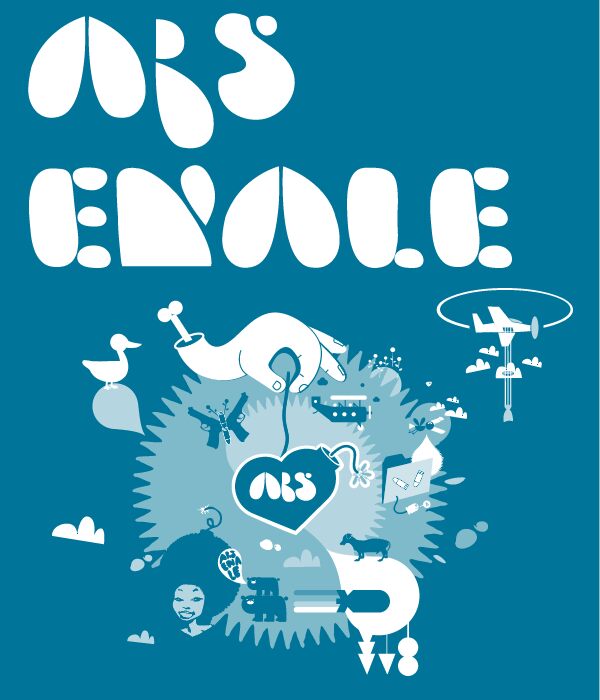
Arsenale Blue od KMzero + Happyloverstown to darmowy krój displayowy z organicznymi zniekształceniami w klimacie późnej psychodelii. Litery wyglądają, jakby zostały wylane, a nie narysowane – z obłymi, napuchniętymi formami, miękkimi spłynięciami i kilkoma gwałtownymi cięciami. Całość sprawia wrażenie gumowej, niekonwencjonalnej i celowo niestabilnej typografii.
Świetnie sprawdzi się na plakatach, ulotkach muzycznych, okładkach zinów, w identyfikacji wizualnej klubów oraz w tytułach, w których napisy mają pełnić rolę formy graficznej, a nie neutralnego nagłówka. Jako darmowy font, doskonale nadaje się też do krótkich nazw na opakowaniach, wlepek i dużych akcentów graficznych, zwłaszcza gdy szukasz miękkich, „roztopionych” sylwetek zamiast czystej geometrii.